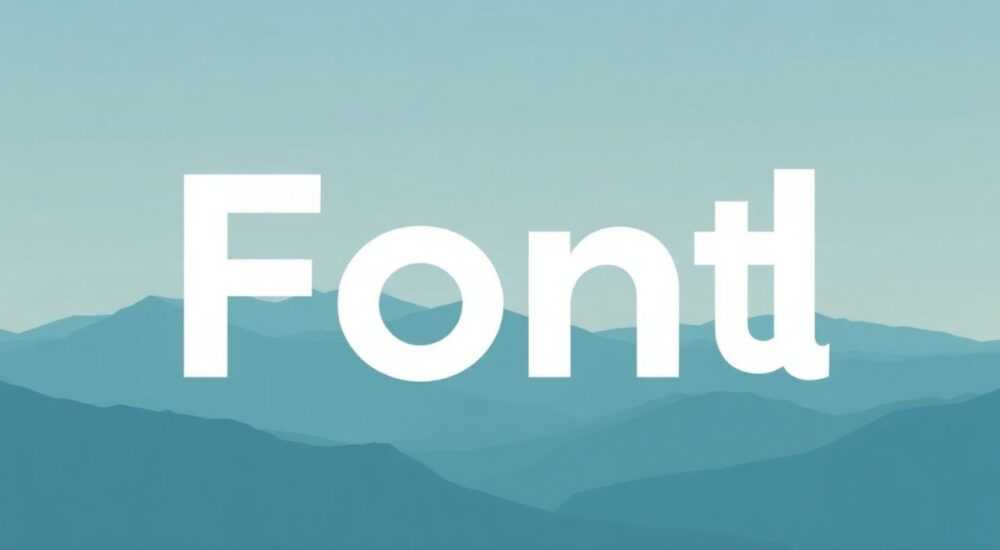
Как поставить шрифт фотошоп
Установка шрифтов в Adobe Photoshop — стандартная задача для дизайнеров, фотографов и всех, кто работает с графикой. Хотя сам по себе Photoshop не хранит шрифты, он использует системные шрифты, доступные операционной системе. Это означает, что чтобы использовать новый шрифт в программе, его нужно установить на компьютер. После установки шрифт автоматически появится в панели инструментов «Текст» в Photoshop. Важно понимать разницу между установкой шрифта на системном уровне и его активацией в самом приложении.
Что такое шрифт в Фотошопе: как программа их видит
Photoshop не является хранилищем шрифтов. Он обращается к библиотеке шрифтов, которая управляется операционной системой. Это значит, что все шрифты, установленные в системе, автоматически становятся доступными в Photoshop после перезапуска программы. Когда вы выбираете инструмент «Текст» (T), список доступных начертаний формируется на основе системных данных.
Шрифты могут быть разных форматов: TTF (TrueType Font), OTF (OpenType Font), WOFF (веб-формат, не поддерживается напрямую) и другие. Photoshop корректно работает с TTF и OTF — это основные форматы, которые рекомендуется использовать. OpenType предлагает больше возможностей: альтернативные глифы, лигатуры, вариации капительных букв и другие типографские функции.
Если шрифт не отображается в списке, первое, что нужно проверить — установлен ли он в системе. Даже если файл лежит на рабочем столе, Photoshop его не увидит. Также важно помнить, что после установки нового шрифта может потребоваться перезапуск Photoshop. Программа считывает доступные шрифты при старте, поэтому новые начертания без перезагрузки могут не появиться.
Какие бывают шрифты: классификация по стилю и назначению
Шрифты делятся на несколько основных категорий: рубленые (серифные), беззасечковые (гротески), рукописные, моноширинные и декоративные. Каждый тип решает свои задачи. Например, серифные шрифты (Times New Roman) хорошо читаются в печатных текстах, а гротески (Helvetica) чаще используются в интерфейсах и заголовках.
Для дизайна важно выбирать шрифт в зависимости от цели: логотип, баннер, книжная обложка или соцсети. Неправильный выбор может испортить восприятие даже идеального макета. В Photoshop можно комбинировать до 5–7 шрифтов в одном проекте, но лучше ограничиться двумя-тремя для сохранения гармонии.
Тип шрифта |
Примеры |
Где применяют |
Серифные |
Georgia, Garamond |
Печатные издания, длинные тексты |
Гротески |
Arial, Roboto |
Веб-дизайн, презентации |
Рукописные |
Brush Script, Pacifico |
Поздравления, логотипы |
Декоративные |
Bebas Neue, Impact |
Заголовки, плакаты |
Как скачать и установить шрифт на компьютер
Перед тем как использовать шрифт в Photoshop, его нужно получить и установить на устройстве. Первый шаг — найти надёжный источник. Существует множество сайтов с бесплатными и платными шрифтами. Среди проверенных ресурсов: Google Fonts, DaFont, FontSpace, Behance и Adobe Fonts (бывший Typekit).
При скачивании обращайте внимание на лицензию. Бесплатный для личного использования шрифт может оказаться платным при коммерческом применении. Особенно важно это для брендов, рекламных кампаний и продажи дизайна. Использование шрифта без лицензии может повлечь юридические последствия.
После скачивания файл шрифта обычно находится в архиве (ZIP). Его нужно распаковать. Внутри будет один или несколько файлов с расширением .ttf, .otf или .woff. Для установки на Windows достаточно кликнуть правой кнопкой мыши по файлу и выбрать «Установить». На macOS — дважды кликнуть по файлу и нажать «Установить шрифт» в предпросмотре.
- Скачайте шрифт с доверенного сайта.
- Распакуйте архив, если необходимо.
- Установите шрифт через контекстное меню (Windows) или предварительный просмотр (macOS).
- Перезапустите Photoshop.
Альтернативный способ: ручная установка через папку шрифтов
Иногда стандартный метод не работает — например, при установке нескольких шрифтов сразу. В этом случае можно вручную скопировать файлы в системную папку:
- Откройте проводник (Windows) или Finder (macOS).
- Перейдите в папку: C:WindowsFonts (Windows) или /Library/Fonts (macOS).
- Скопируйте туда файлы шрифтов (.ttf или .otf).